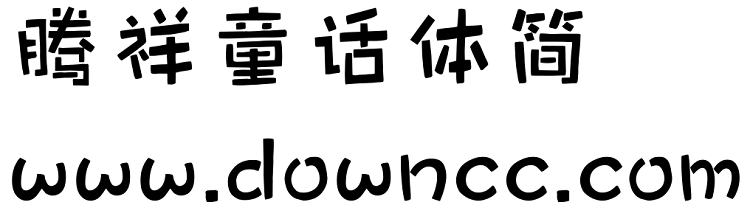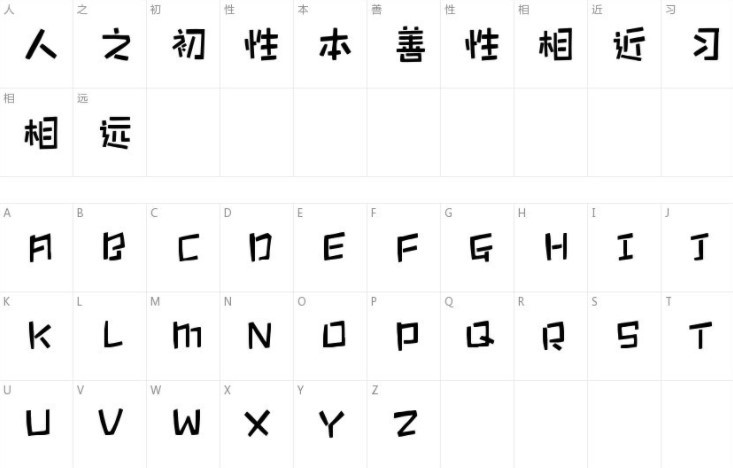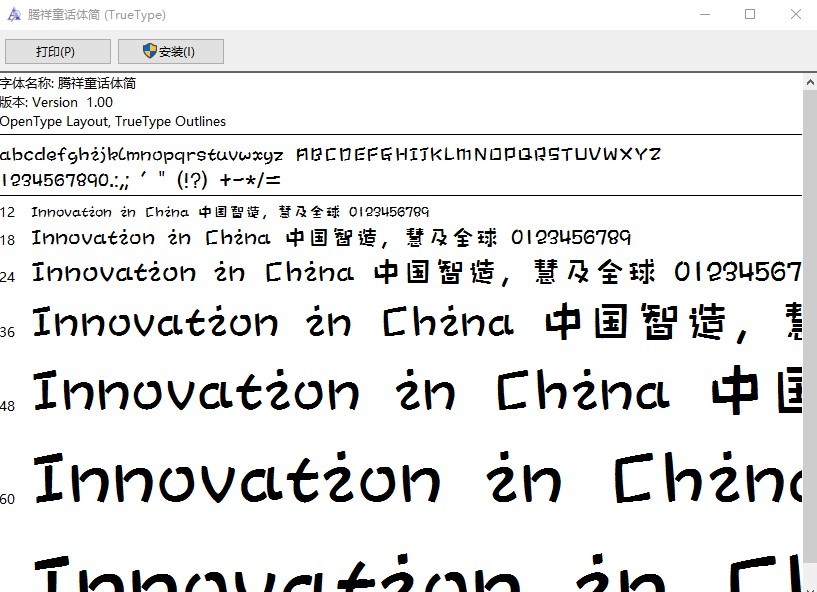
騰祥童話體簡體免費版作為騰祥字體的其中一款簡體版中文字體,筆畫字形看起來精致又可愛,錯落有致,簡單流暢,充滿趣味性,是極具個性的藝術(shù)手寫字體,在設(shè)計領(lǐng)域里被廣泛運用,尤其深受年輕朋友們的喜歡,值得推薦!
騰祥童話體簡是由騰祥字庫全新開發(fā)的常規(guī)簡體中文字體,該字體筆畫粗細適度且錯落有致,筆畫與筆畫之間適度留白形成疊壓使字體看起來更清晰,增強可讀性。結(jié)構(gòu)夸張隨性,但又有一定之規(guī),歪斜的筆畫以筆畫與筆畫間的協(xié)調(diào)為根本,彰顯整款字稚趣盎然、活潑可愛。能夠適用于藝術(shù)設(shè)計、包裝印刷、簽名設(shè)計、圖形設(shè)計等領(lǐng)域!
字體名稱:騰祥童話體簡
風格:美術(shù)體,手寫體
字體特點:稚趣、流暢、書寫童真
適用范圍:印刷用字、顯示用字